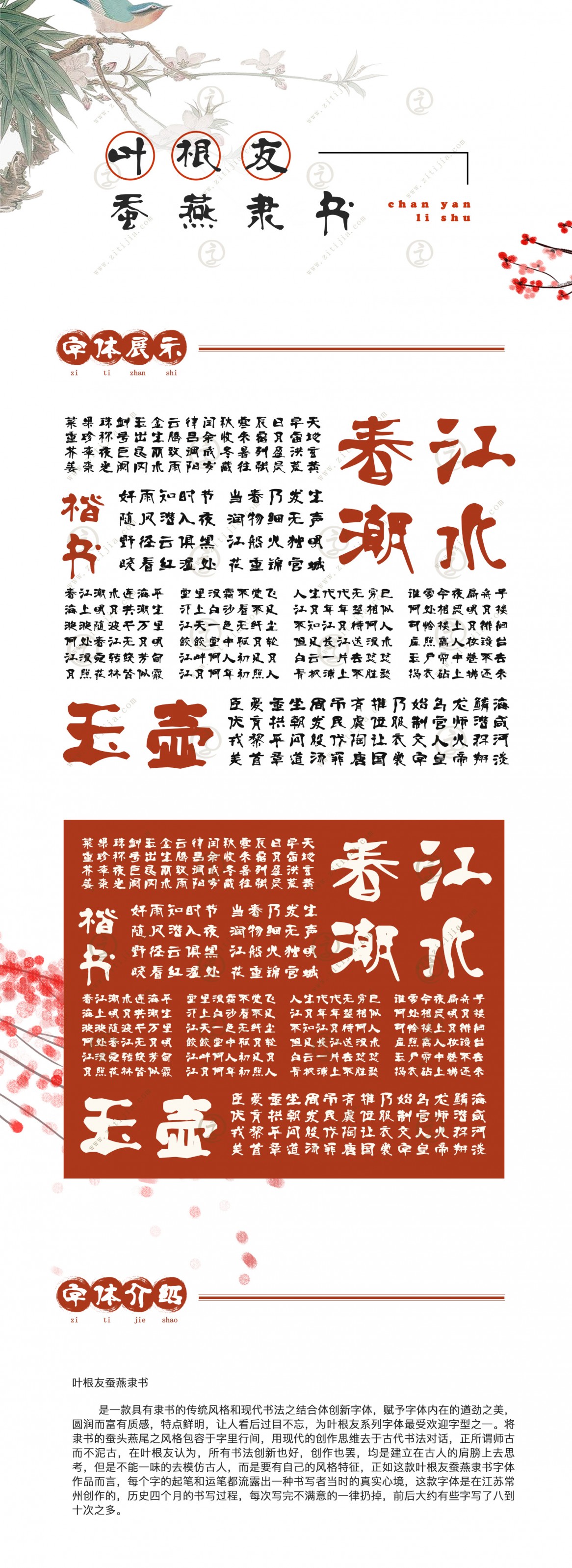
葉根友蠶燕隸書
字體作者:葉根友
創(chuàng)作年代:2008年
字體字數(shù):6763個中文漢字以及其他英文字母和阿拉伯?dāng)?shù)字
字體介紹
葉根友蠶燕隸書是一款具有隸書的傳統(tǒng)風(fēng)格和現(xiàn)代書法之結(jié)合體創(chuàng)新字體,賦予字體內(nèi)在的遒勁之美,圓潤而富有質(zhì)感,特點鮮明,讓人看后過目不忘,為葉根友系列字體最受歡迎字型之一。將隸書的蠶頭燕尾之風(fēng)格包容于字里行間,用現(xiàn)代的創(chuàng)作思維去于古代書法對話,正所謂師古而不泥古,在葉根友認為,所有書法創(chuàng)新也好,創(chuàng)作也罷,均是建立在古人的肩膀上去思考,但是不能一味的去模仿古人,而是要有自己的風(fēng)格特征,正如這款葉根友蠶燕隸書字體作品而言,每個字的起筆和運筆都流露出一種書寫者當(dāng)時的真實心境,這款字體是在江蘇常州創(chuàng)作的,歷史四個月的書寫過程,每次寫完不滿意的一律扔掉,前后大約有些字寫了八到十次之多。